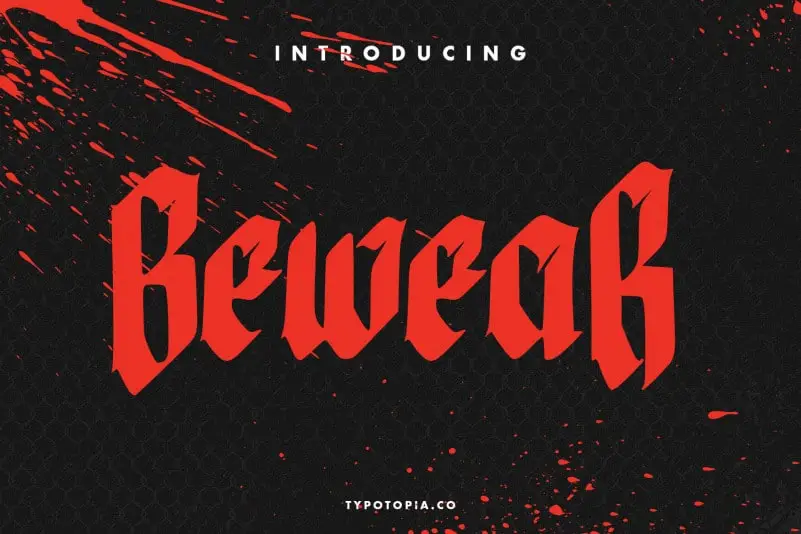
Bewear Creepy Font – Download Grátis
Introduzimos a fonte “Bewear Creepy Font”, uma fonte de exibição única e interessante do designer typotopia. Sua peculiaridade se destaca em sua forma sinistra e irônica, perfeitamente adaptada para textos de grande tamanho que se destacam, como cabeçalhos ou design gráfico impactante. A “Bewear Creepy Font” é um recurso visual inovador, projetado para criar uma atmosfera assustadora no meio da comunicação visual. Esta fonte tem o poder de transformar qualquer texto em um elemento chamativo e memorável, especialmente quando usada em aplicativos como sites de publicidade ou banners de televisão. Com sua elegância grotesca e personalidade intrincada, a “Bewear Creepy Font” é uma excelente escolha para aqueles buscando algo diferente e criativo. É perfeita para textos que buscam chamar atenção na internet ou em espaços visuais, proporcionando um desafio visual impressionante aos leitores.